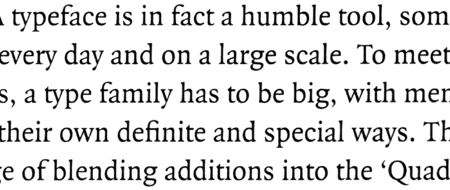
Schriften für ein Interview-Magazin
Die Scala wollte ich hier auch schon vorschlagen :-)
Das ist eine gut lesbare Textschrift, die aber auch eine gute Portion Eigenwilligkeit mitbringt. Außerdem gibt es sie mit und ohne Serifen, von Light bis Black. Da kann man schon viel mit machen ...
Folgende Schriften sind in der 100-beste-Schriften-Edition enthalten:
Neue Helvetica
Stempel Garamond
Sabon
Frutiger
Bauer Bodoni
Futura
ITC Officina
Gill Sans
Univers
Optima
ITC Franklin Gothic
FF Meta
FF DIN
FF Letter Gothic
FF Scala
Syntax
Bell
FF Dax
Swift
News Gothic
FF Quadraat
Ok, diese Schriften funktionieren als Fließtextschriften:
Neue Helvetica
Stempel Garamond
Sabon
Frutiger
ITC Officina
Univers
FF Letter Gothic
FF Scala
Syntax
Swift
Quadraat
News Gothic
FF Meta
ITC Franklin Gothic
Und diese Schriften würde ich als Headline- und Auszeichnungsschriften ausprobieren:
Bauer Bodoni
Futura
Gill Sans
(FF DIN)
FF Dax
Quadraat
Quadraat ergänzt für Joshua ;)
Und warum fehlt die Quadraat völlig in Deiner Liste? :twisted:
Ich würde die gerne mal im Fließtext sehen, und interessante Auszeichnungsschnitte hat sie auch. Bisher ist sie mir leider bloß auf Buchumschlägen begegnet, da aber schon öfter. Und jedesmal bin ich dann enttäuscht, wenn ich das Buch aufschlage, und doch nur wieder eine Garamond sehe.
Entschuldige lieber Joshua :-) Wir können sie gerne mit aufnehmen. Ich hatte die Liste nur einen Hauch reduziert, um unseren Magazinfreund nicht durch seine komplette Schriftensammlung zu jagen. ;-)
+1 :) Bringhurst spricht jedenfalls überaus freundliche Worte über sie und die zugehörige Sans in seiner Hitliste von Textschriften ... :)
Falls ich mich richtig erinnere war sie in der ersten Auflage (die zweite hab ich nicht) von Buchstaben kommen selten allein von Indra Kupferschmid zu sehen. Und falls ich das Buch zufällig finde kann ich nachschauen. ;-)
Stimmt schon, es müsste nicht immer eine klassische Garamond sein, aber die Quadraat wäre mir für ein z.B. Roman zu dynamisch, zu eng und zu kompakt, hätte mir hierfür zuviel Eigenheit. Es gibt aber doch auch konventionellere Oldstyles wie die Documenta, Merlo, Verdigris … die nach massivem Einsatz schreien.
Die hochverehrte Minion stört mich in diesem Zusammenhang auch, für mich keine Buchschrift – ihre Enge ist mir zu augenfällig.
Zum Thema: Als Schrift in einem Magazin kann ich mir die Quadraat Großfamilie aber sehr gut vorstellen.
Oder: Eine sehr lebendige Slab ist die Chaparral Pro, kann ich mir für ein Interview-Mag auch gut vorstellen. Und die hat zumindest "jeder"´in den Grundschnitten.
ich bin zwar kein großer gill fan, aber gerade hier könnte ich sie mir gut vorstellen.
das thema passt, die farbekombination passt, riecht irgendwie alles nach schmuddel.
vorallem die extrabold display oder ultra bold für die healdline auf der linken seite und
ggf. die bold für frage und eine schöne ausgeglichene serif für die antwort.
Klar, immer paßt sie natürlich nicht. Und daß da noch ganz andere Schriften unterbenutzt sind, steht wohl außer Frage!